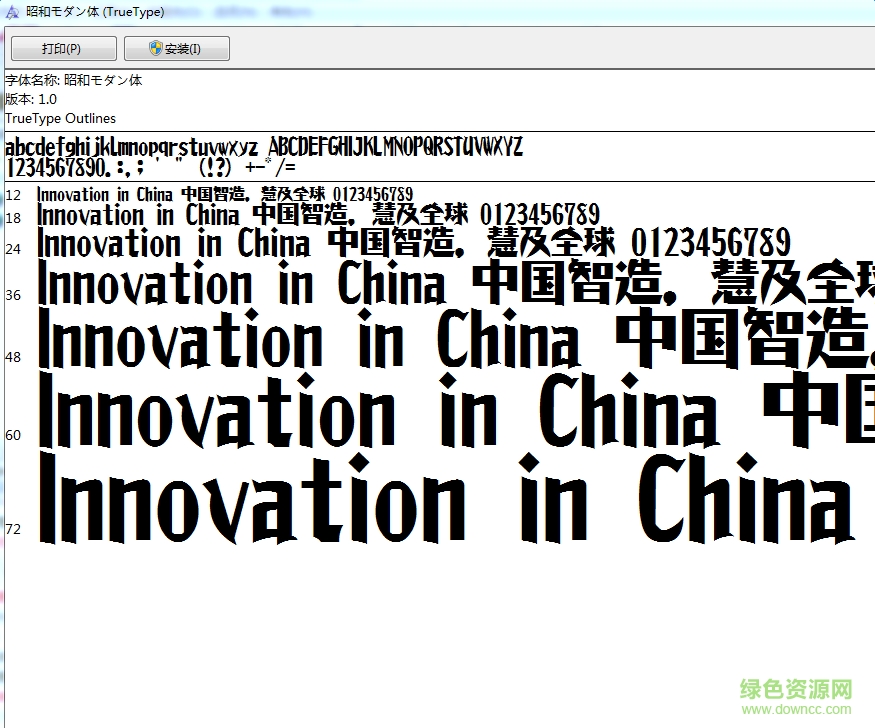
日本昭和体字体是一款古典粗黑风格字体软件,昭和体笔画工整,撇捺尾部细腻,非常独特有创意,整体效果比较醒目耐看,感兴趣的朋友欢迎来绿色资源网下载体验!
日本昭和体字体是一款应用于艺术设计方面的简体中文字体,该字体笔画粗壮,尾部的甩尾有力且有丰富的笔触细节,大字效果突出且引人注目;并且最大程度还原作者书写字形,细节表现完整,且字库完整,可以广泛应用于名片设计、新闻媒体、宣传海报、ppt、影视制作以及内容用字等领域。
该字体笔画细腻,每个字体所占空间一致,给人非常清爽简单的感觉,非常的好看!